В этом модуле мы учились делать бесшовный паттерн, узнали, каким он может быть. Я выбрала работать над паттерном в духе Уильяма Морриса и над строчными буквами русского алфавита королевской антиквы в двух начертаниях силуэтном и схемовом. Мы сделали много эскизов, рисунков и перенесли всё в фонтлаб. Получившийся шрифт теперь можно использовать, а ремезы в духе Морриса бодро вьют гнездо на платке.
Сначала мы начертили все буквы с помощью циркуля и линейки
затем по кальке сделали силуэт
для каждой буковки
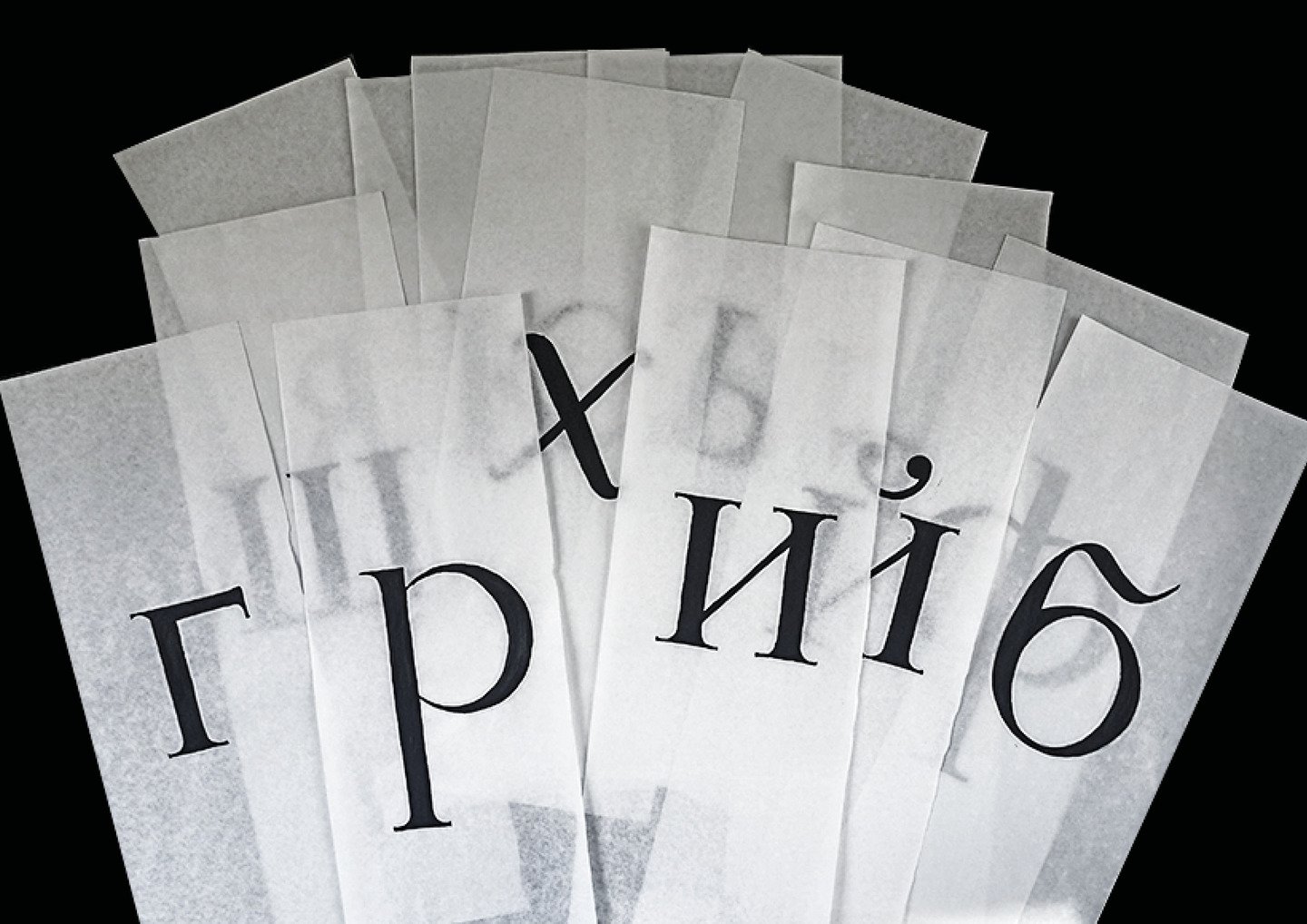
Потом началась работа над паттерном.
Были сделаны эскизы, выбраны наиболее удачные, был нарисован (и таким образом немного изучен) ремез, была выбрана цветовая палитра и замешаны оттенки в баночках, ну а потом ремез был перерисован в элемент паттерна на финальном листе, а затем собран и сам паттерн
Сначала делались линейные эскизики на основе фотографий, а затем мы нарисовали финальный эскиз ремеза и ивы уже в цвете
используемые в паттерне цвета (делала темперой)
итоговый элемент паттерна в двух цветовых решениях
итоговый паттерн и вплетённые слова